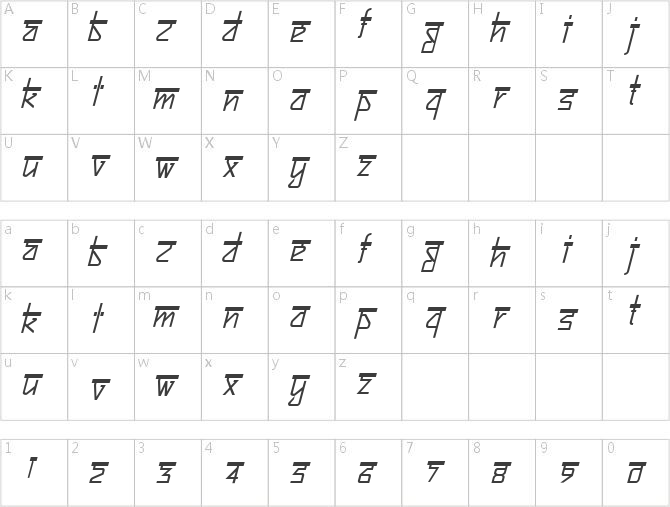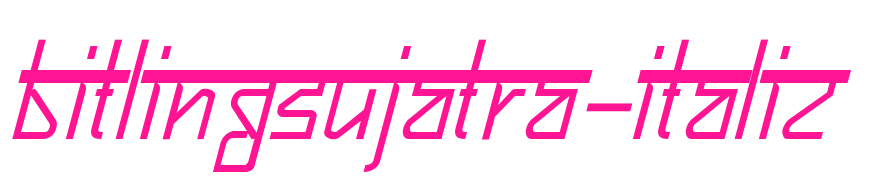
Bitlingsujatra-Italic 詳情頁(yè)
Bitlingsujatra-Italic字體字庫(kù)是一款讓人賞心悅目、百看不厭的英文字體,適合各類廣告和產(chǎn)品包裝設(shè)計(jì)應(yīng)用,字體大小0.02MB,格式為ttf字體,上傳用戶是@小咖,作者/版權(quán)方為未知